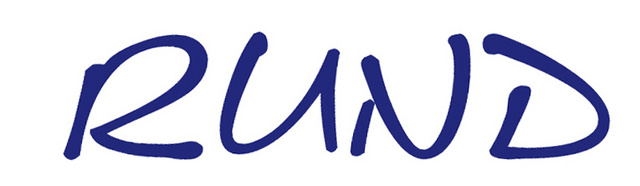
Kennt jemand diese Schreibschrift?
vielleicht erkennt jemand diese Schreibschrift und kann sie mir nennen, bzw. eine ähnliche, die kostenlos (auch kommerziell in einem Logo) verwendet werden darf?
Aber so ganz passen tut sie ja nicht. Zumindest tauchen u. a. das R und B in der Form weder in den Minuskeln noch in den Majuskeln der verlinkten Schrift exakt so auf. Dass die Le Asterix Pate stand, ist aber dennoch ziemlich sicher.
Meines Wissens gibt es nur den einen, oben verlinkten Schnitt der Le Asterix. Das spricht in meinen Augen eher dafür, dass die Schrift von dem Grafiker entsprechend modifiziert und angepasst wurde.